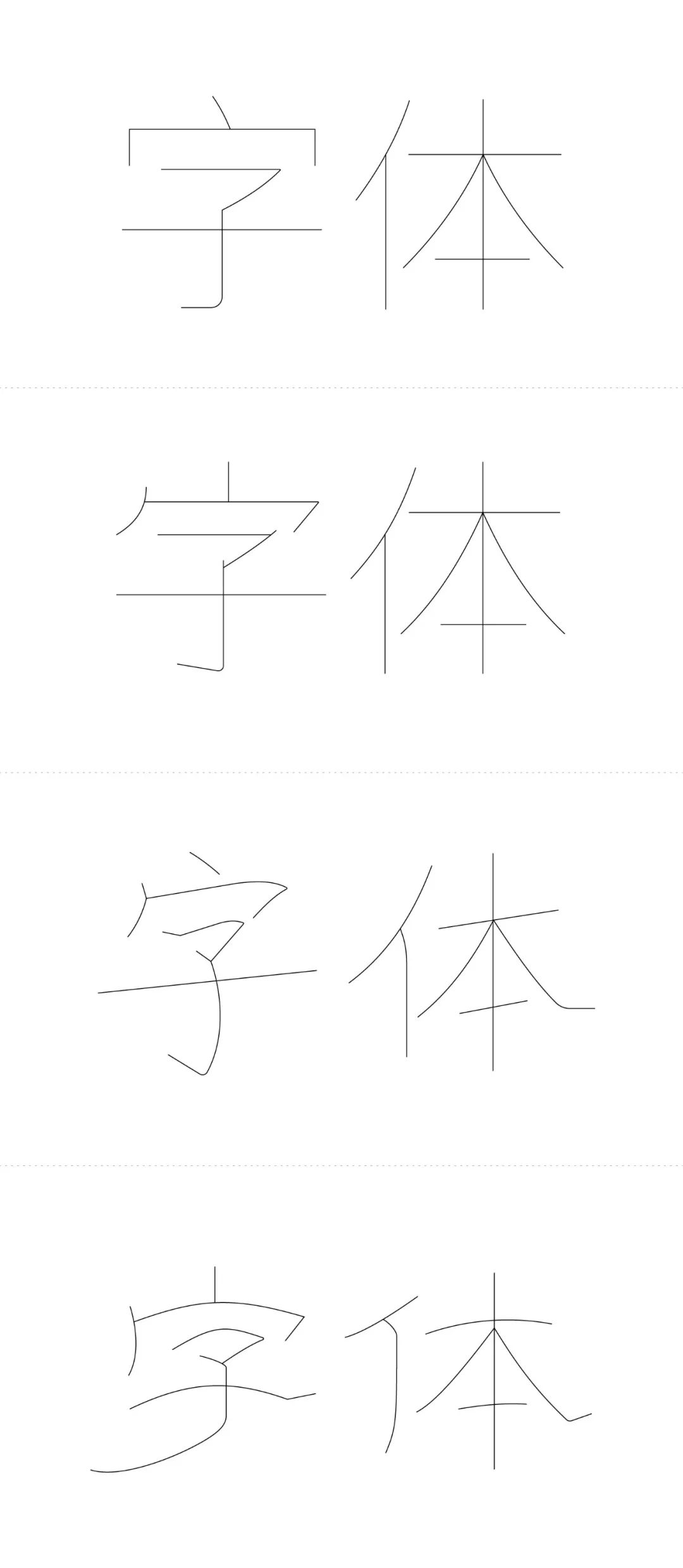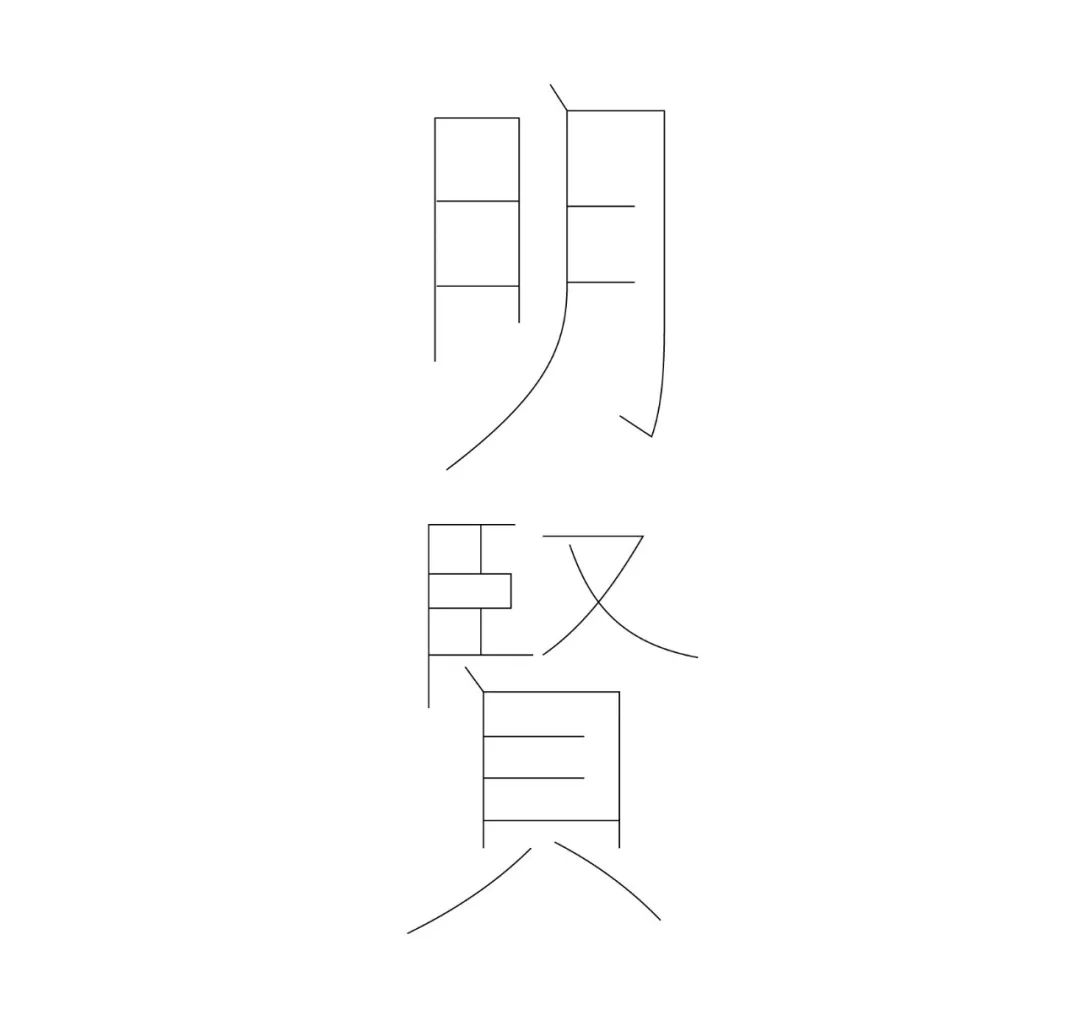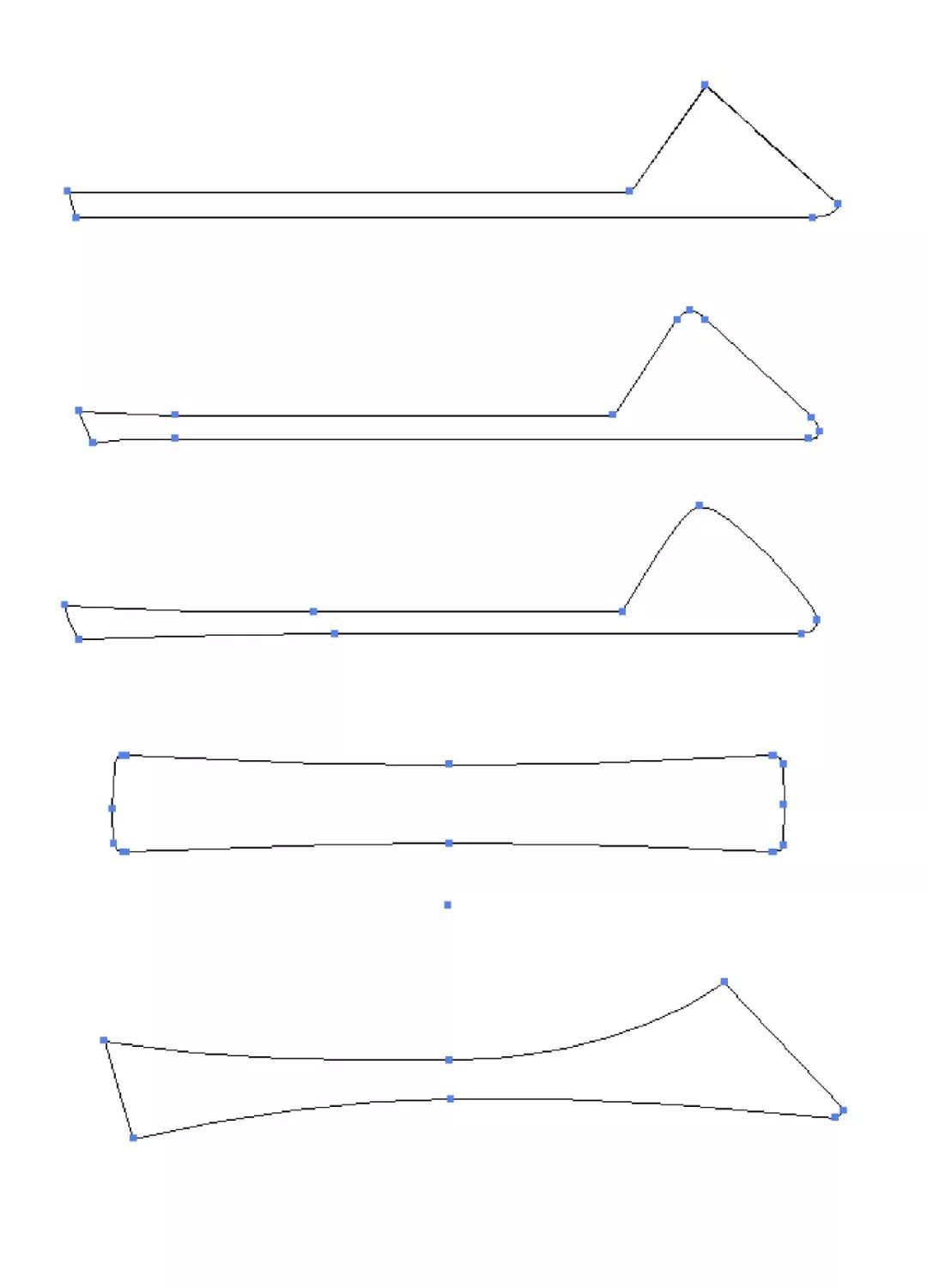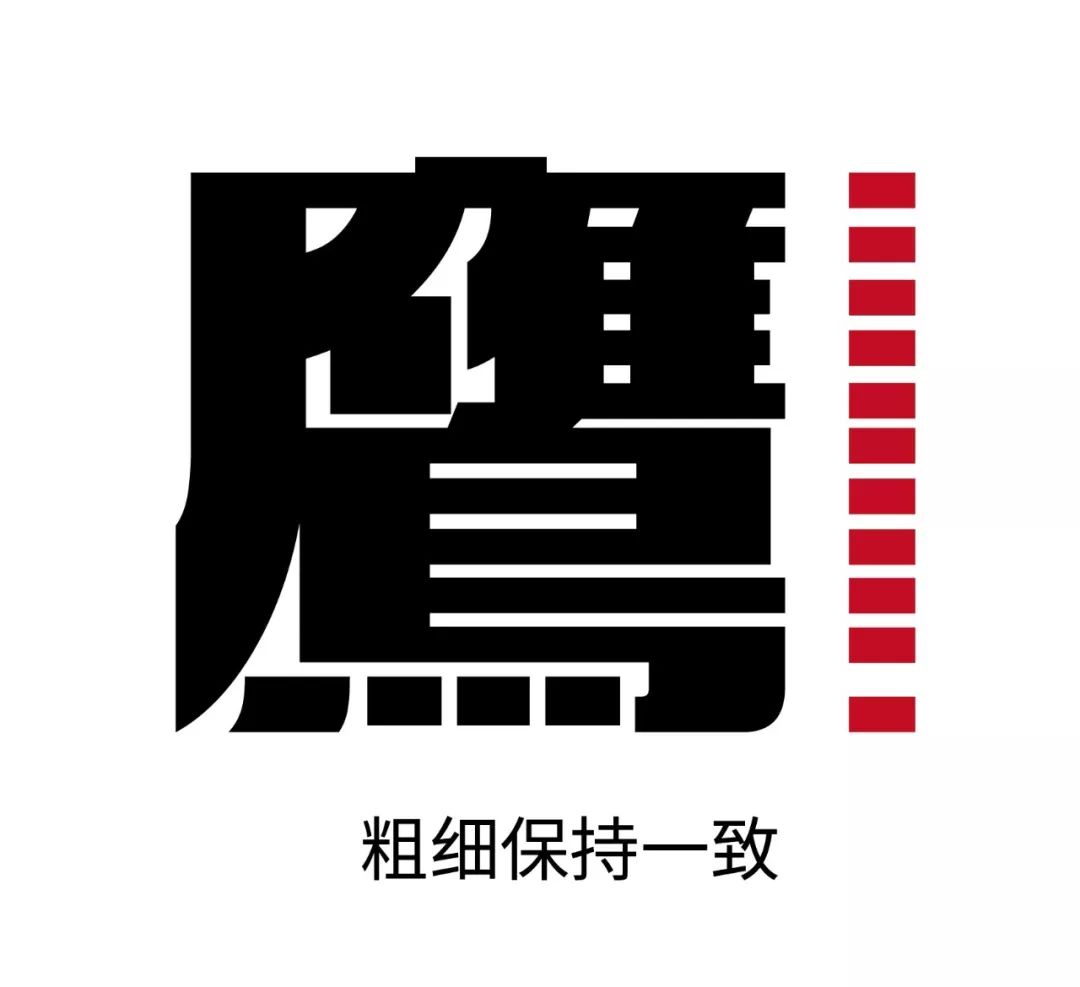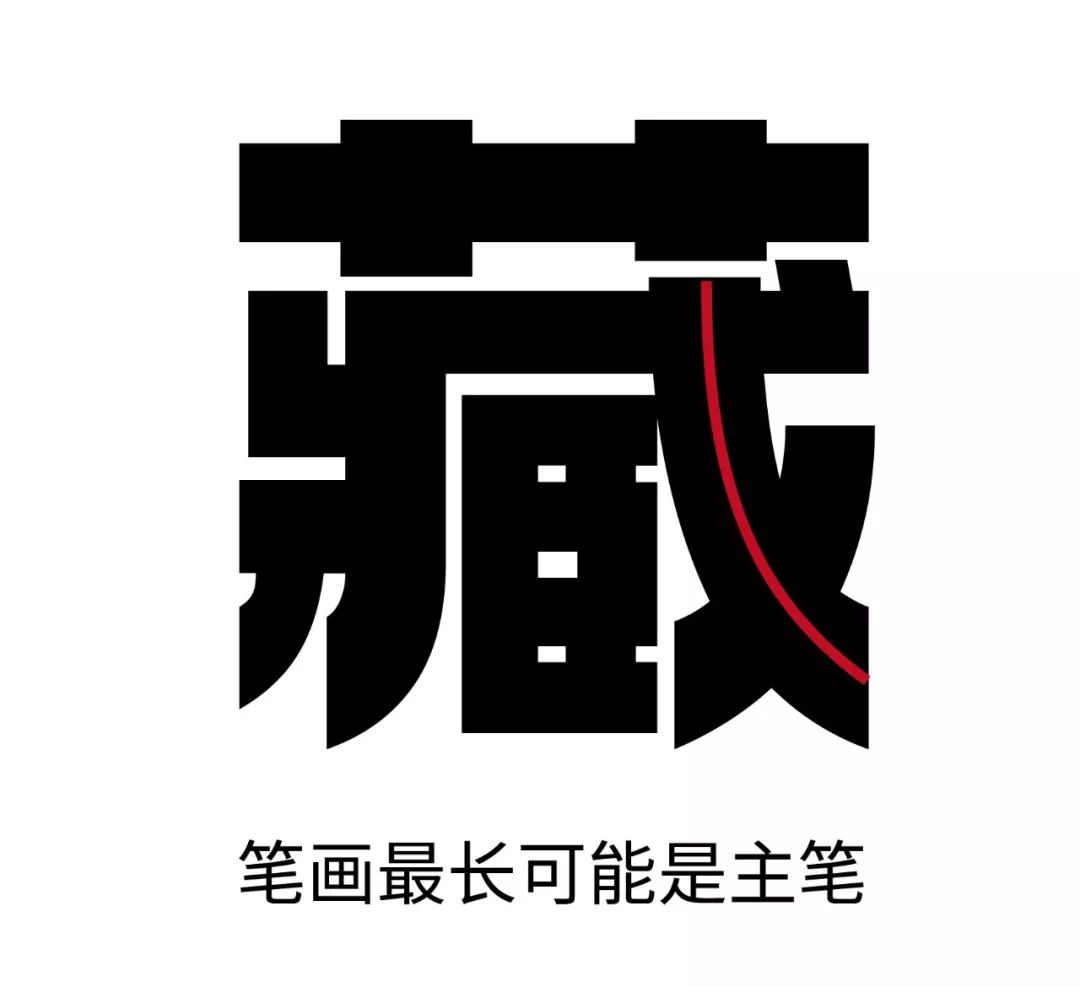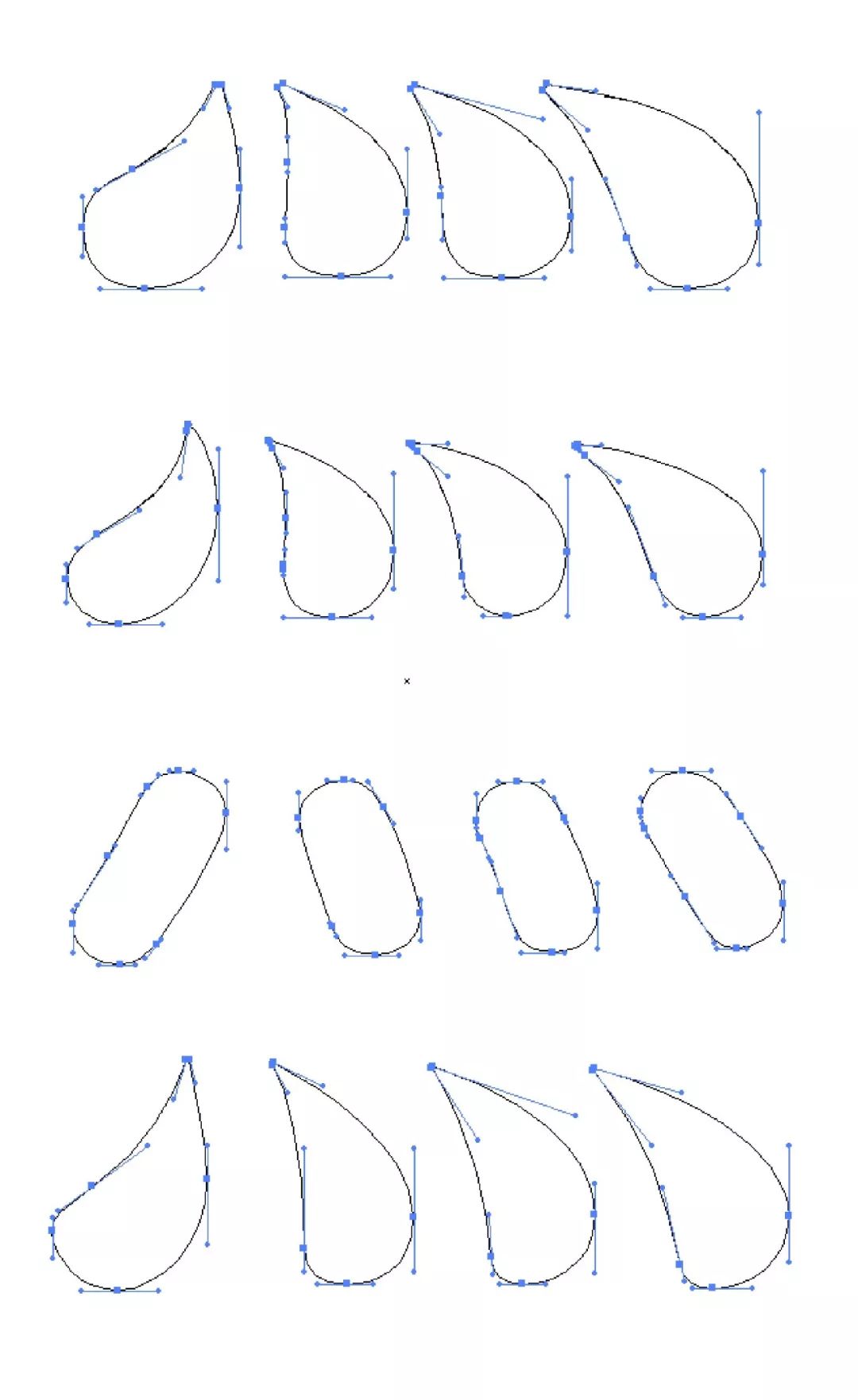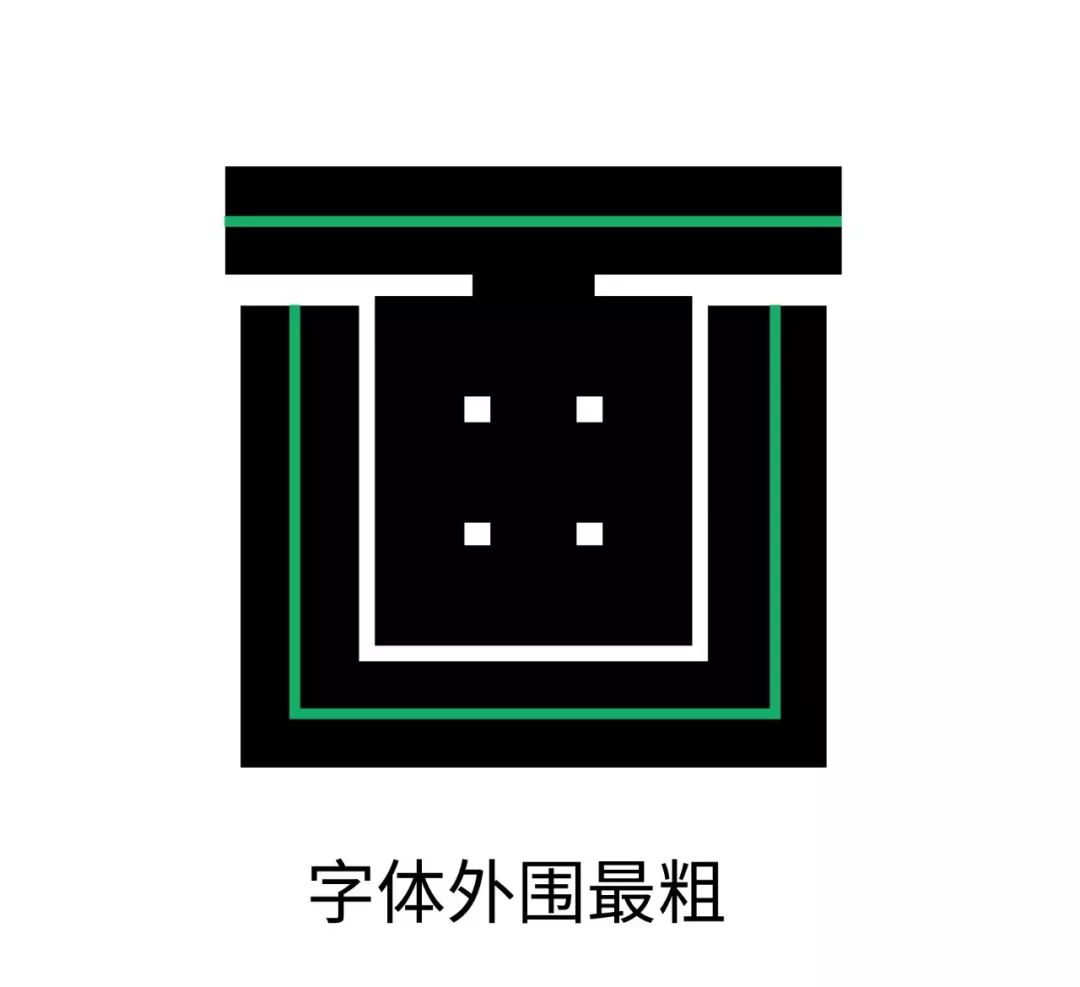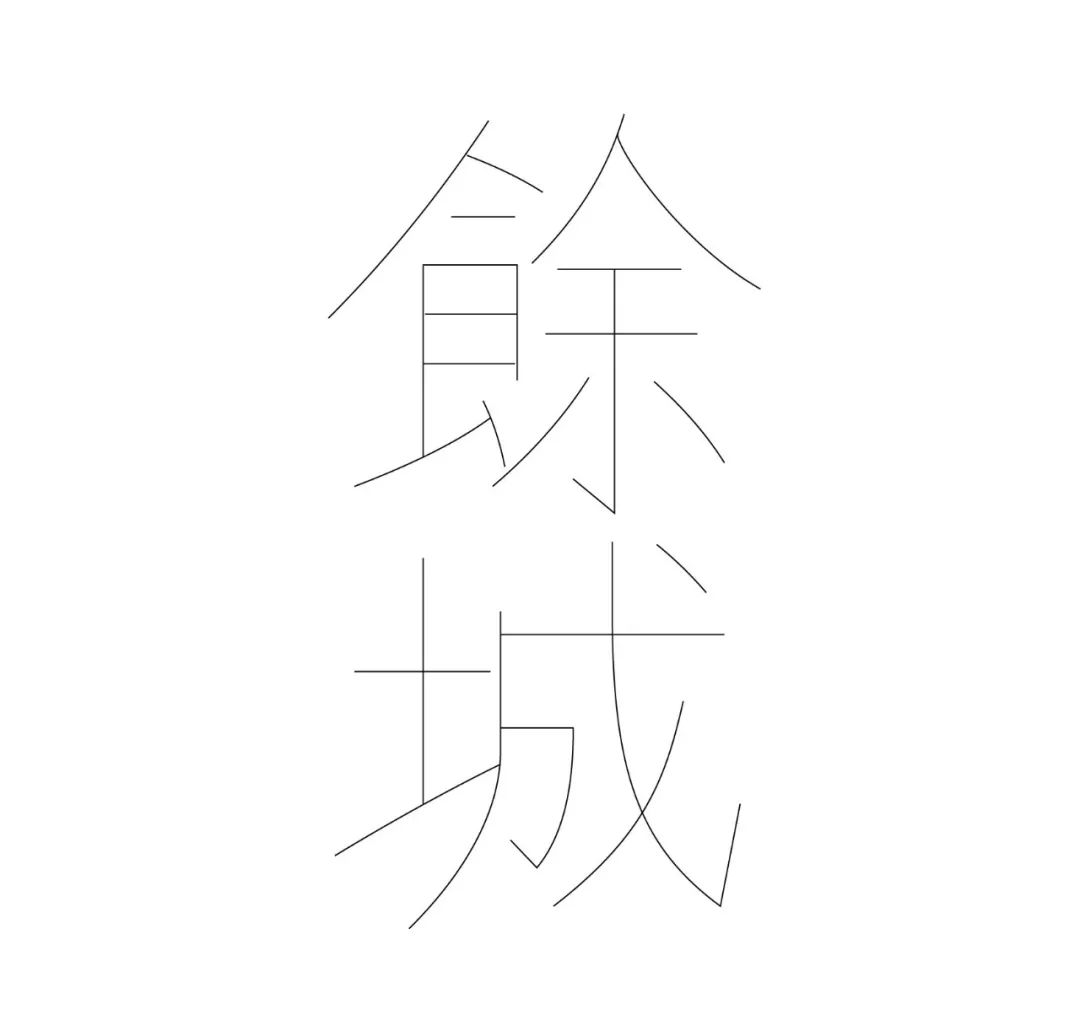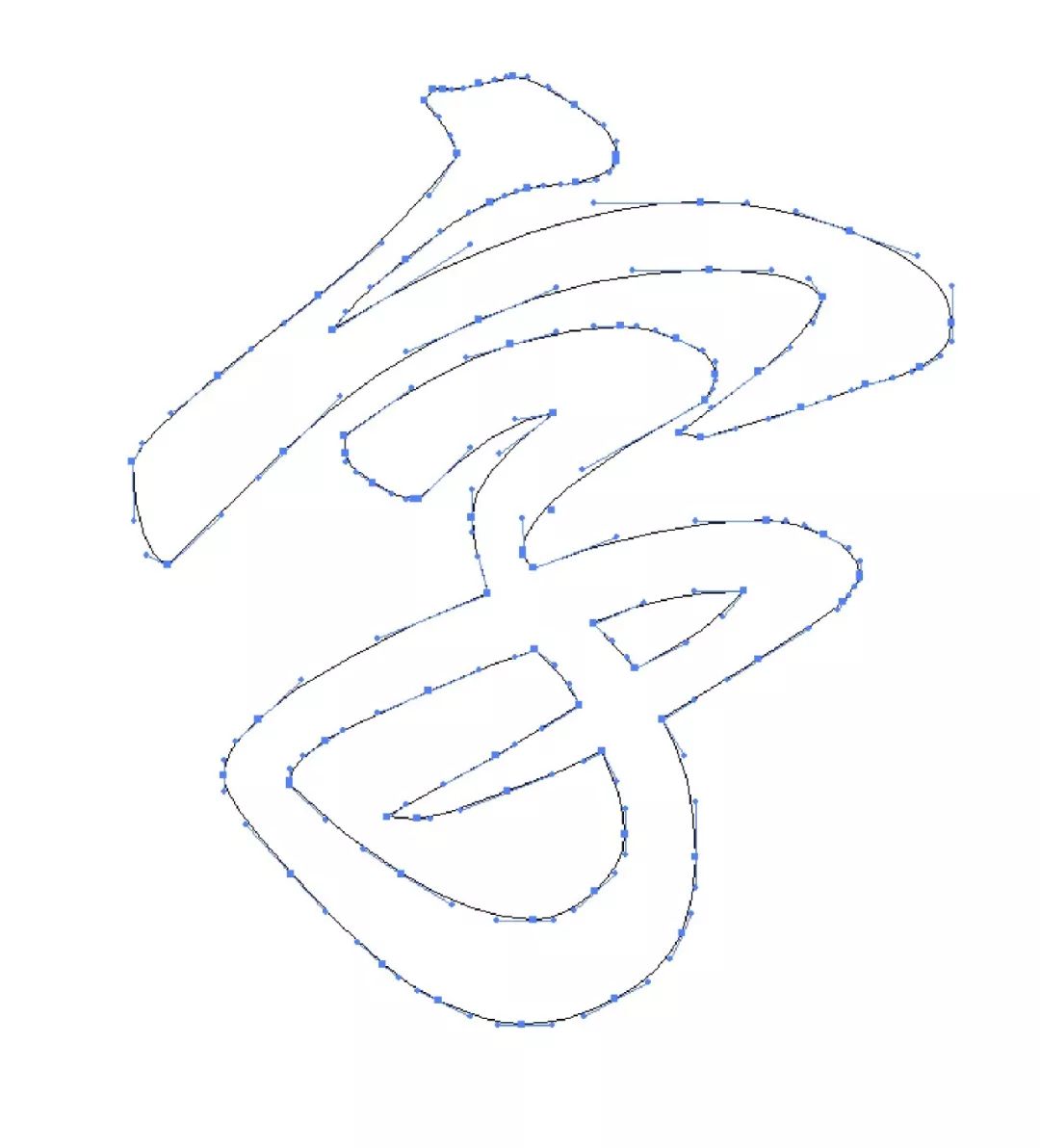
字体设计知识分享,这才是正确的做字方法~
许多初学者无法正确树立专业的字体设计知识,甚至已经学了字体好几年的设计师,因为路子实在太野,仍旧对于细节无法正确认知。
所以这次我们决定来一次彻底的专业扫盲,建立正确的做字方法。
字体骨骼相对来说并不是简单的就可以熟练掌握的,因为在这一项当中,包含的内容较多,中宫字面重心自然没有必要再次谈及,许多教程和书籍当中都会谈到这些概念,虽然看了许多遍的你仍然还是一头雾水,这是因为字体的大部分概念是模糊的,需要长期的在实践中探索。是经验的产物。
那我们这里说字体骨骼,其实仍然是模糊的,泛谈概念会不可避免的陷入到:脑子懂了,手不会这样的境地中。
而且初学者可能简单的结构是勉强可以掌握的,比如基础黑体,是最乏味平常的一种结构。
这样的结构你应该是可以掌控的。
这样的结构容易使人看久了比较容易腻,而且没有独特的结构呈现。我们再来看一下其它的结构方式。
那么上面的这四种结构其实不看具体的笔画粗细特征等等,我们也能大概看出来它们具体属于哪些种类,可能前两种不好猜,但是后两种是很好猜的,分别为楷体和隶书。
什么叫做经典,只看字体骨骼就能看出来属于什么字形,这就是经典的力量。
那么问题来了,许多同学并没有书法经验,书写经验也只有以前上学时抄作业的技能水准,结构并不好做,所以我这里提供一种方法,从古籍资料当中寻找字骨。
巧了,我这里有一本金瓶那啥梅的古籍资料,不要想歪,我们只是来看一下当中的书体。
忍不住想问我要全本的同学忍住,我不会给的。
从中提取你需要的字,特征未必要同它一致,但是结构可以借用一下,而且不存在侵权。
再来看一下其它字形的结构。我们再次勾勒一下。
锚点的排布很多同学在实际操作当中经常忽略,不足够重视,所以专门来写一下。
锚点排布我们遵从的第一原则是“锚点数量极简”,即用最少的锚点,完成预想中的笔画或者曲线。
我们来看一下在字库当中锚点的呈现。注意观察。
锚点的作用无非有两个。
第一个,两点形成线段,即锚点控制线条,笔画的起始与终点。
第二个,锚点常常作用于直线或曲线的转折处,即控制线条的走向角度。
最经常发生的其实不是上面这样的错误,这样的错误示范很多同学都可以自发的规避掉,事实上,更考验人的部分往往在于更复杂的笔画,因为你往往不知道到底多少锚点才是正确答案。
比如点。
以上都是正确答案,不同的形态会产生不同的锚点数量需求,如果你还不知道正确答案到底是什么,就要动手去尝试来画,仔细比对,总结经验。
再来说一下锚点的位置,大部分时候,锚点的位置是我们首要要考虑到的,甚至对于有经验的设计师来书,锚点的位置一旦形成,笔画的形态自然就在心里形成轮廓。
所以锚点的位置一定要反复尝试,我们来看一下不同的笔画特征中锚点位置如何发生变化,哪些又是一直没变的。
一句话总结,锚点的位置是按照笔画的需求决定的,位置决定了你可以做最少的锚点还是要多出好几个锚点。
锚杆和锚点在功能上相互补足,不同的是,锚杆基本上是专用于控制曲线。
那么锚杆的角度有什么要注意的呢,这个问题就牵扯到了上一个问题,许多同学之所以不能用最少数量的锚点画预想中的曲线,就是因为锚点的位置没选择好,锚杆的角度没有设置好。
锚杆的第一原则是,水平或垂直。
当然不是所有笔画都适合这两个角度方向,但是这两个方向往往控制了曲线的主干部分,位置在视觉上,水平或垂直的锚杆可以使曲线具柔韧性。
仔细观察以下锚杆的角度,你可以尝试这样去做,这个属于标准做法。
下面示范了一个相对来说比较复杂的字形,所以在当中有一些锚杆的角度可以仔细看一下。
一些较为特异的笔画特征,就不太涉及一定要锚杆角度水平或者垂直,不要勉强。
这些只是一个帮助你规范操作的一个手段而已。回到设计的目的,尽量还原你想要的笔画形态即可。
就如同我们看到的一些优秀的书法字库,它就很少采用锚杆水平或者垂直,因为书法的形态就很复杂,保证还原笔画的形态才是第一位要做的。
之所以我们要专门说一下遵从视觉原则,是因为我碰到过很多同学都有这样的困惑。
不明白粗细保持统一和粗细保持一致到底有什么区别。
不明白宋体当中横笔很细的时候如何控制横笔粗细。
不明白有的字横笔很多时应该如何处理。
等等很多类似于这样的疑问。其实回答是非常简单的,就是以视觉为准(眼神不好使的同学自动关闭此文)。
比如粗细保持统一和粗细保持一致的区别。
这个就是粗细保持统一的一个做法,注意横笔的粗细。
但是粗细保持统一往往有一个上下文理解,就是这个字你要跟其它字在视觉上保持一致,这个是背后隐藏的意思。
下面这个呢,横笔粗细我全部调整成为一致。
这个也不是错误的做法,但是跟上面对比一下,会发现细节不够清晰,而且这个横笔很难再调整更粗,粗细有局限性。
那第一种做法有什么技巧吗?
两个原则,主副笔原则。外围最粗原则。
先说主副笔,很好理解,主要的笔画和次要的笔画,也就是主要笔画可以突出,次要笔画可以弱化。
剩下的问题就是如何区分主副笔。
一般情况,注意只是一般情况,一个字当中最长的那个笔画就是主要笔画,可以进行强调。
再说一下外围最粗原则,即字体各个部件或字体整体的外围笔画最粗。人眼首先接收的轮廓形态,所以外围决定了这个字有多粗。
这期内容比较偏理论更多,总的来说,养成良好的设计习惯,虽然有一些地方是很细微的,但是长远来说,就怕你不够认真,什么事都习惯凑合。